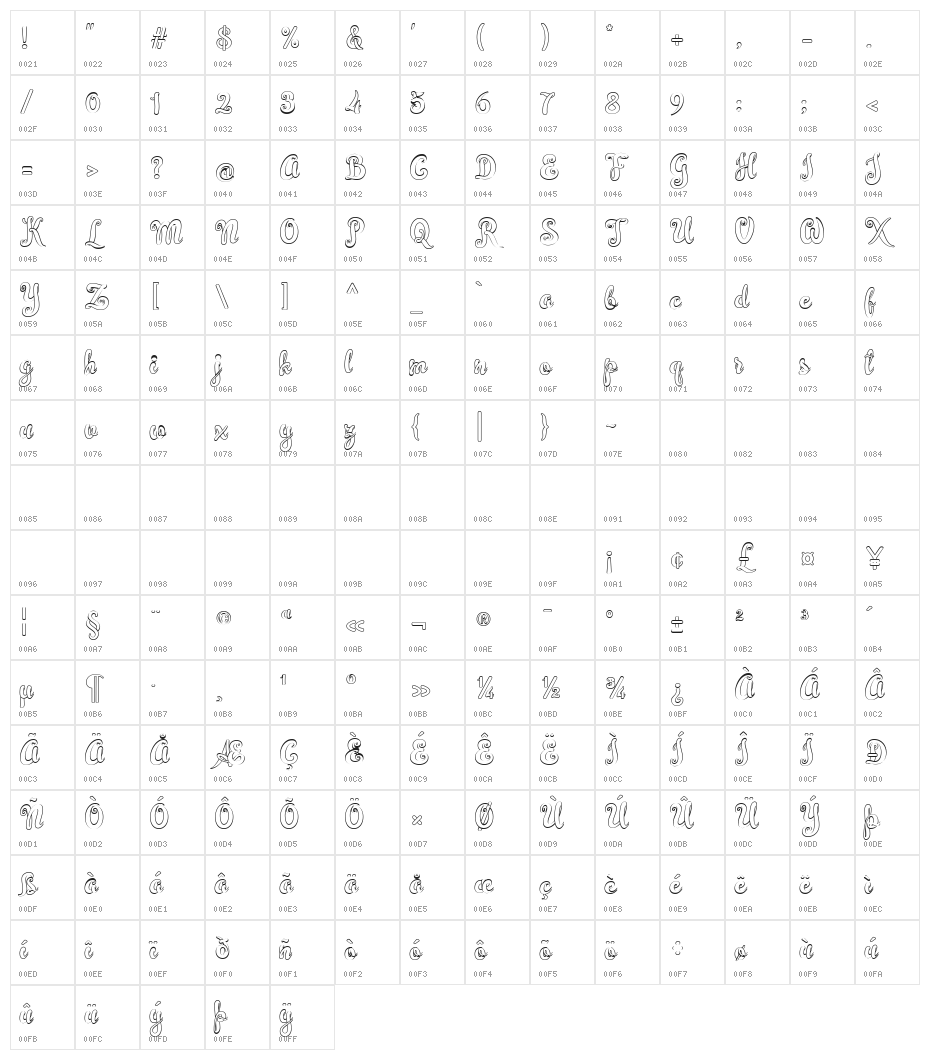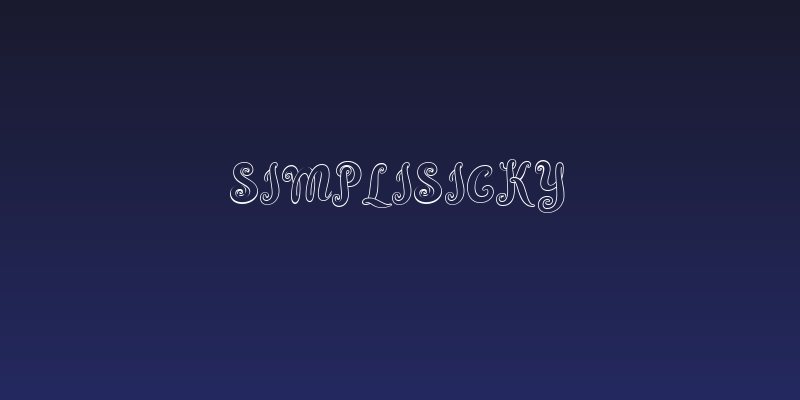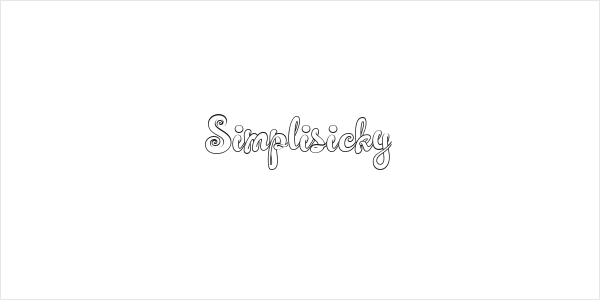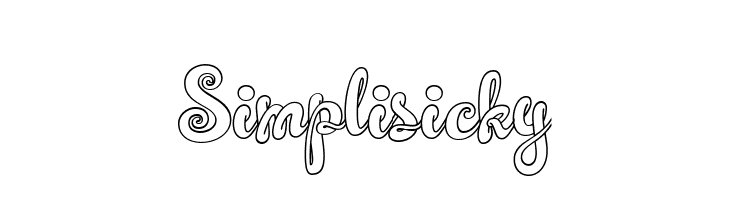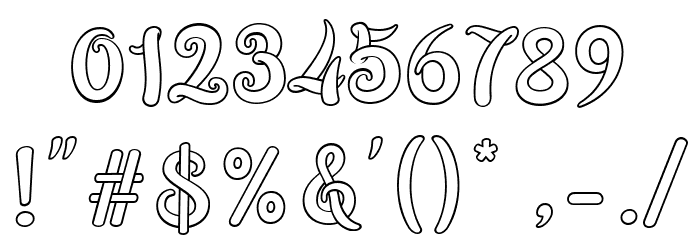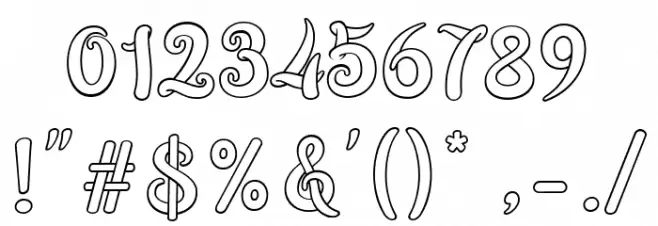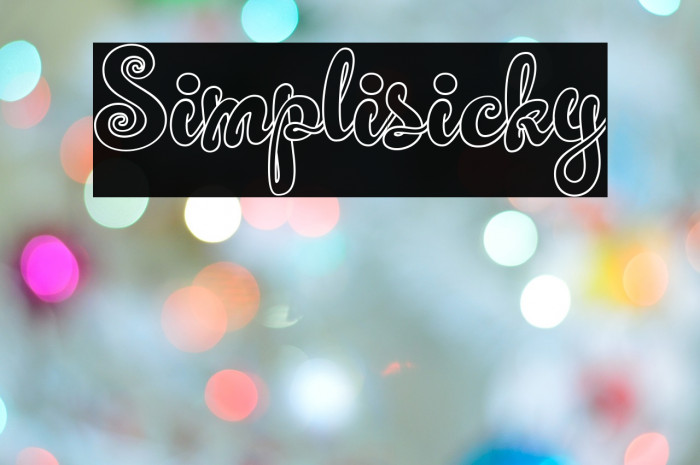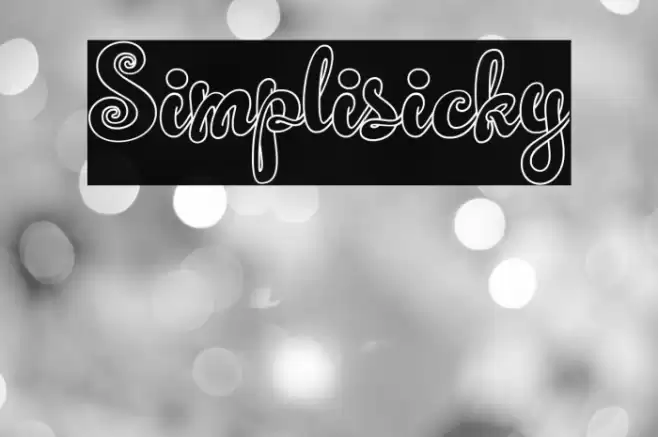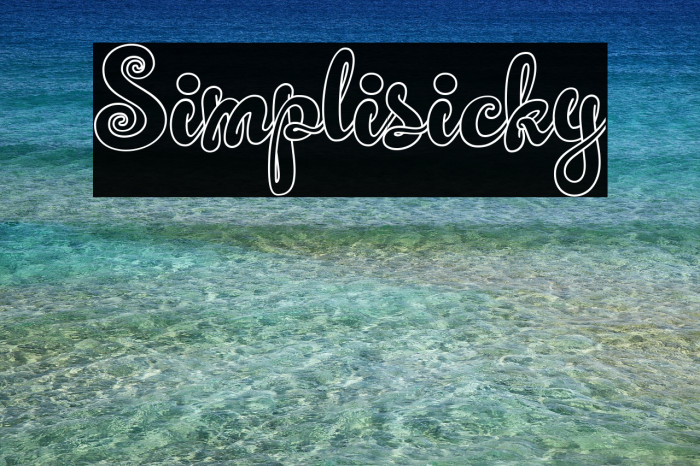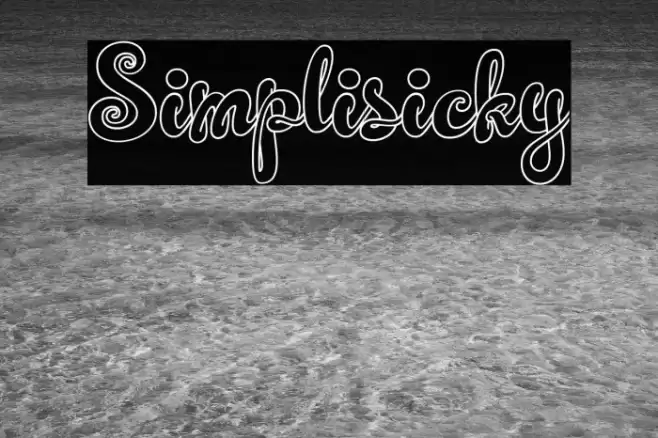
Simplisicky Font
✎ Curly
| الفئات | Curly |
| النمط العام | Playful, Whimsical, Hand-drawn |
| حالة الاستخدام | Headlines, Logos, Creative projects |
| مشاريع مقترحة | Ideal for children's books, party invitations, creative branding, and playful designs. |